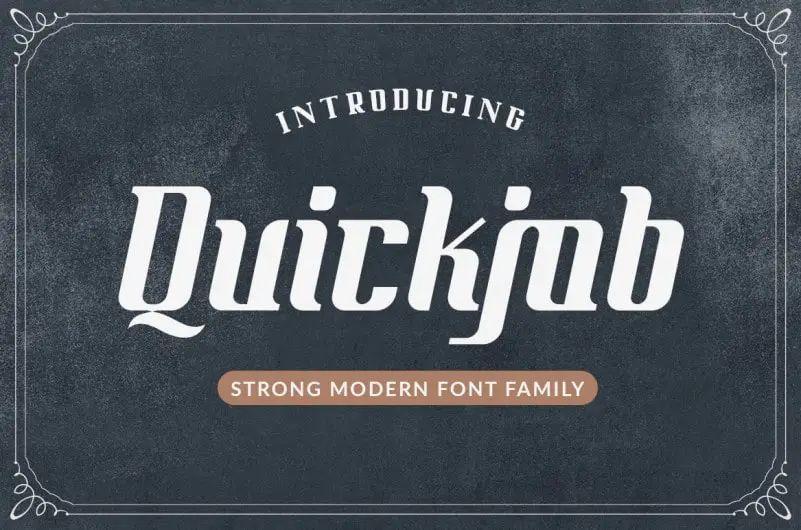
Quickjob Display Font – Download Grátis
A Quickjob Display Font é uma escolha incrível para quem busca destacar seus designs. Essa fonte vem com seis estilos diferentes e está pronta para transformar qualquer projeto de design, independentemente do seu propósito ou formato. Seja para criação de marca, assinaturas elegantes, cartões de convite românticos, logotipos inspiradores ou etiquetas únicas – a Quickjob Display é perfeita para qualquer uso que você tenha em mente. A sua força e elegância são certamente ideais para quem deseja um elemento visual atraente em seus projetos. Com esta fonte, os designs podem subir de nível sem necessariamente aumentar o esforço ou tempo dedicado à criação. Ela é perfeitamente adaptável para qualquer situação gráfica, tornando-a uma escolha inteligente tanto para iniciantes quanto para designers experientes. Seja qual for a sua necessidade, a Quickjob Display está lá para lhe ajudar a chegar ao topo com estilo e elegância.